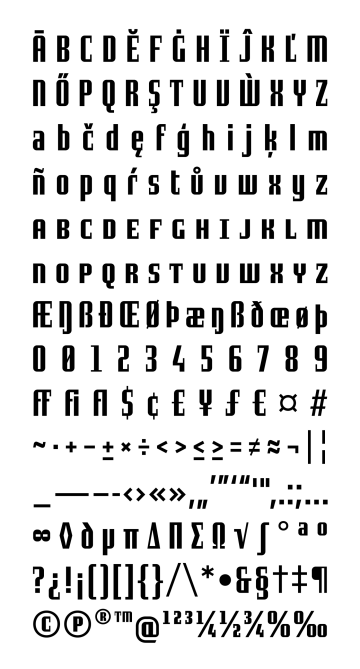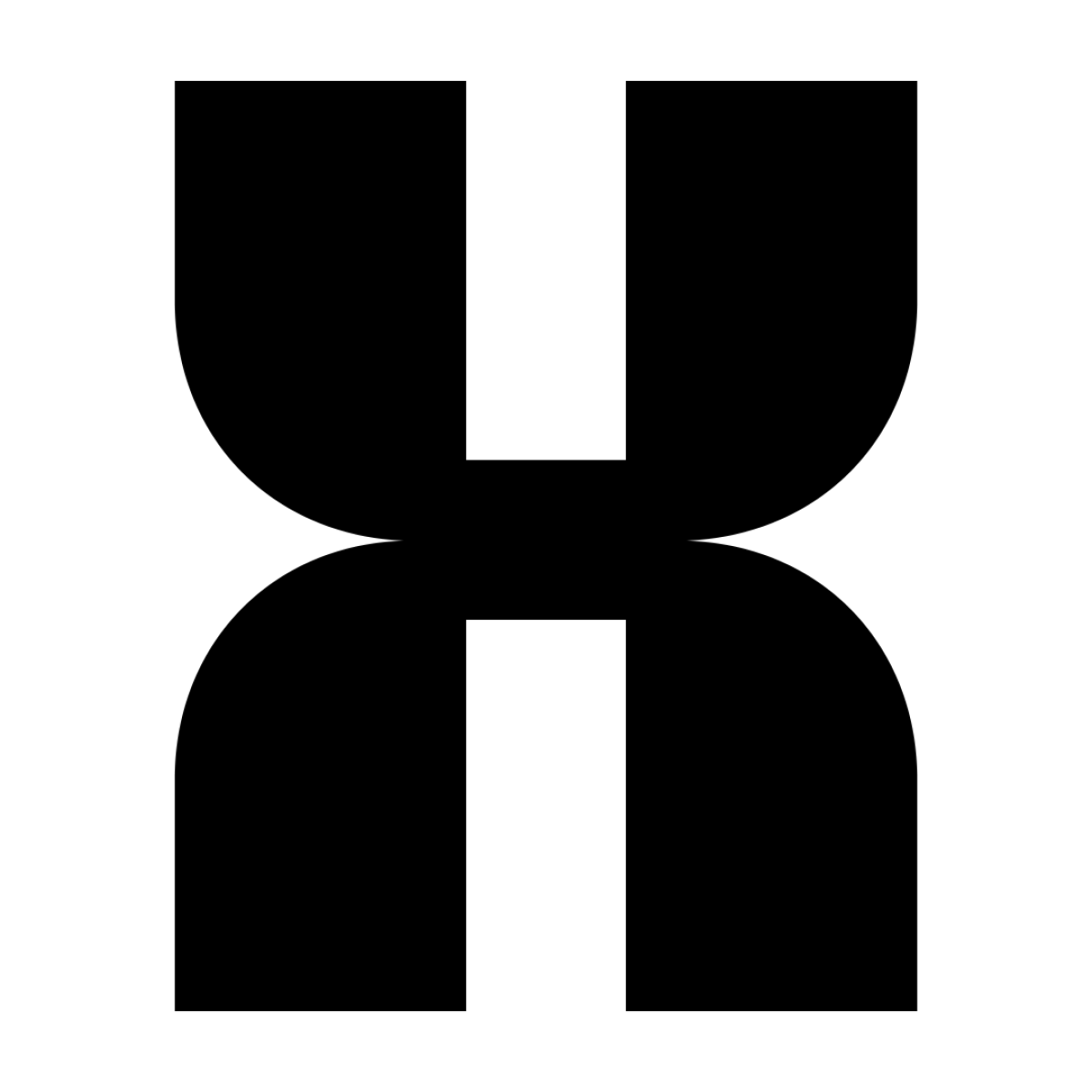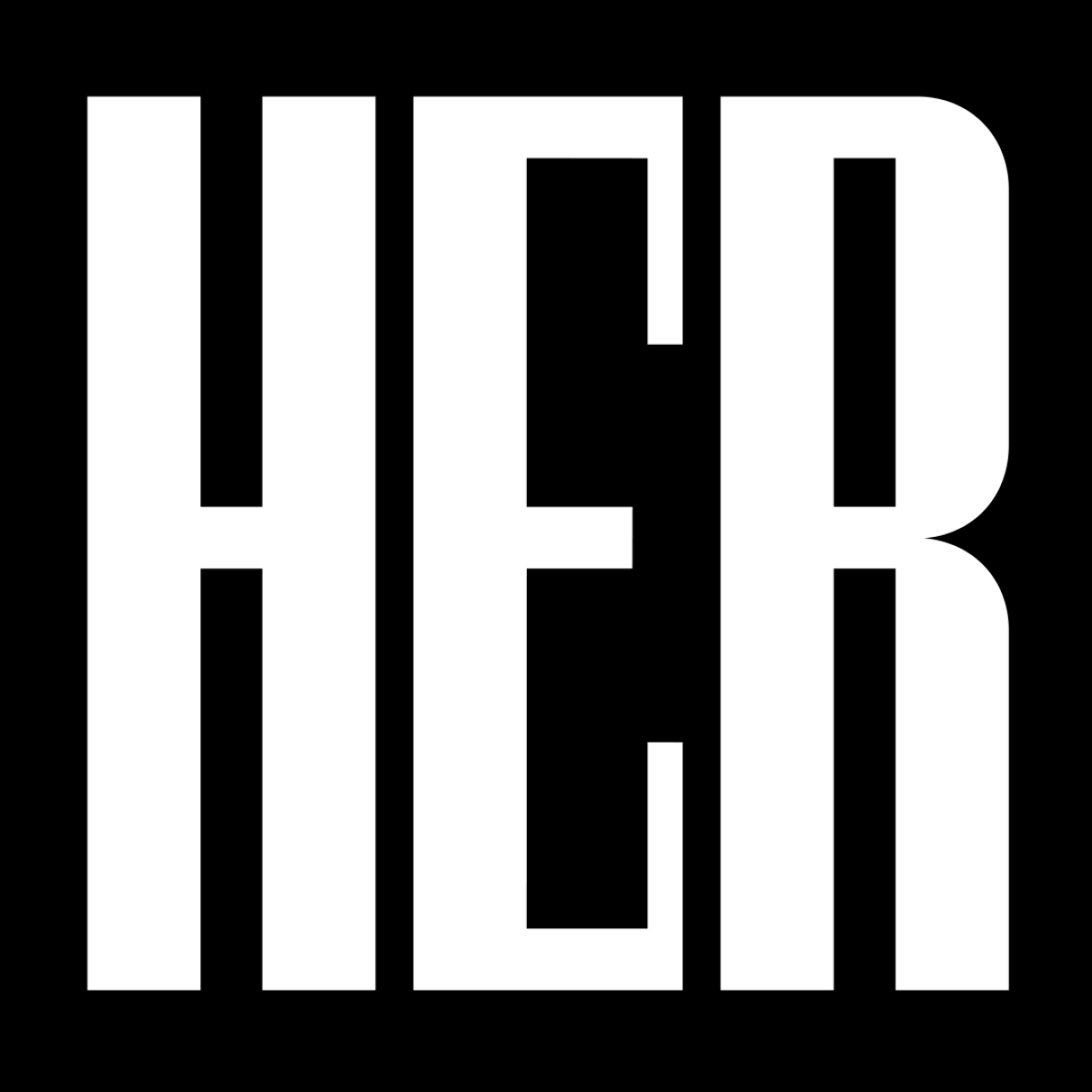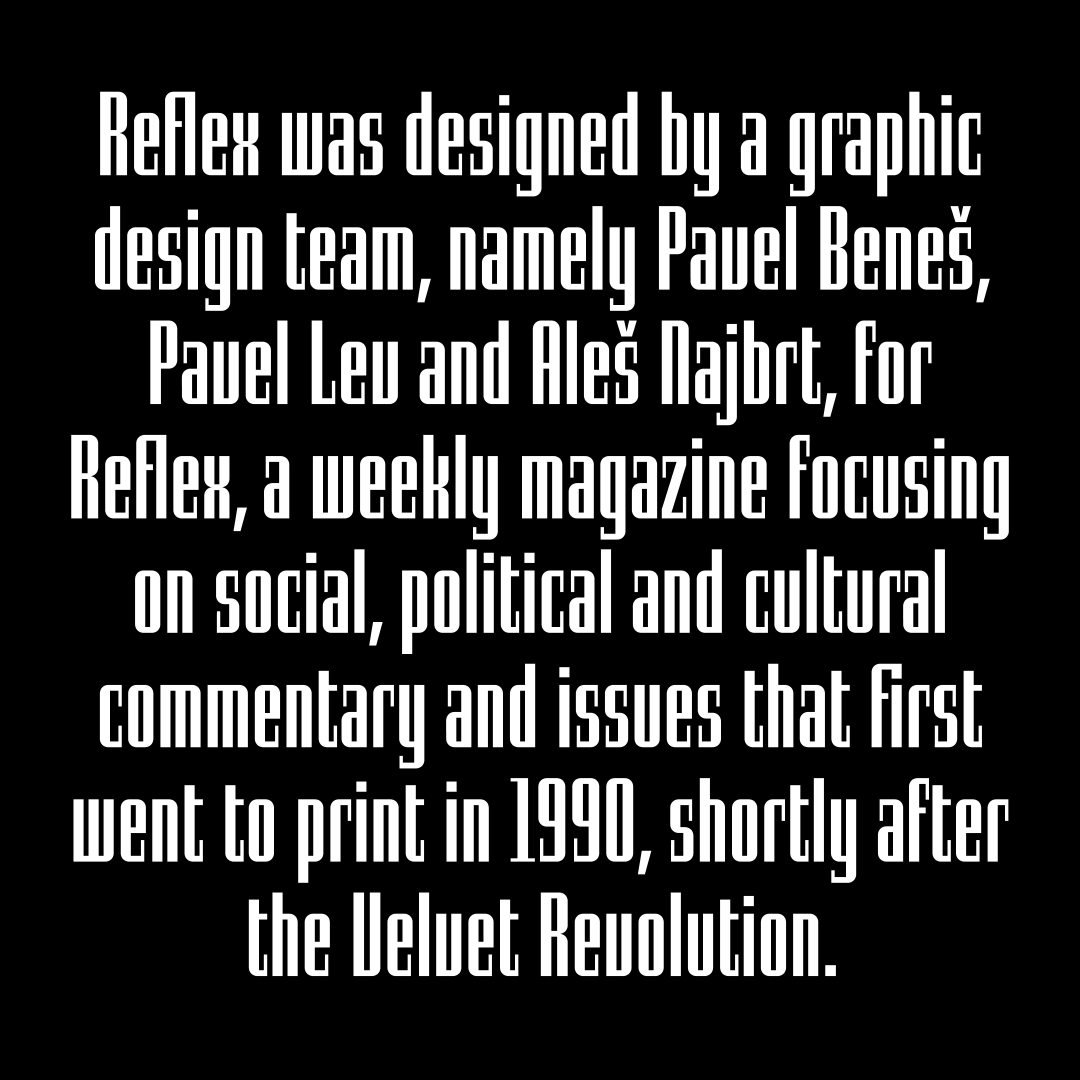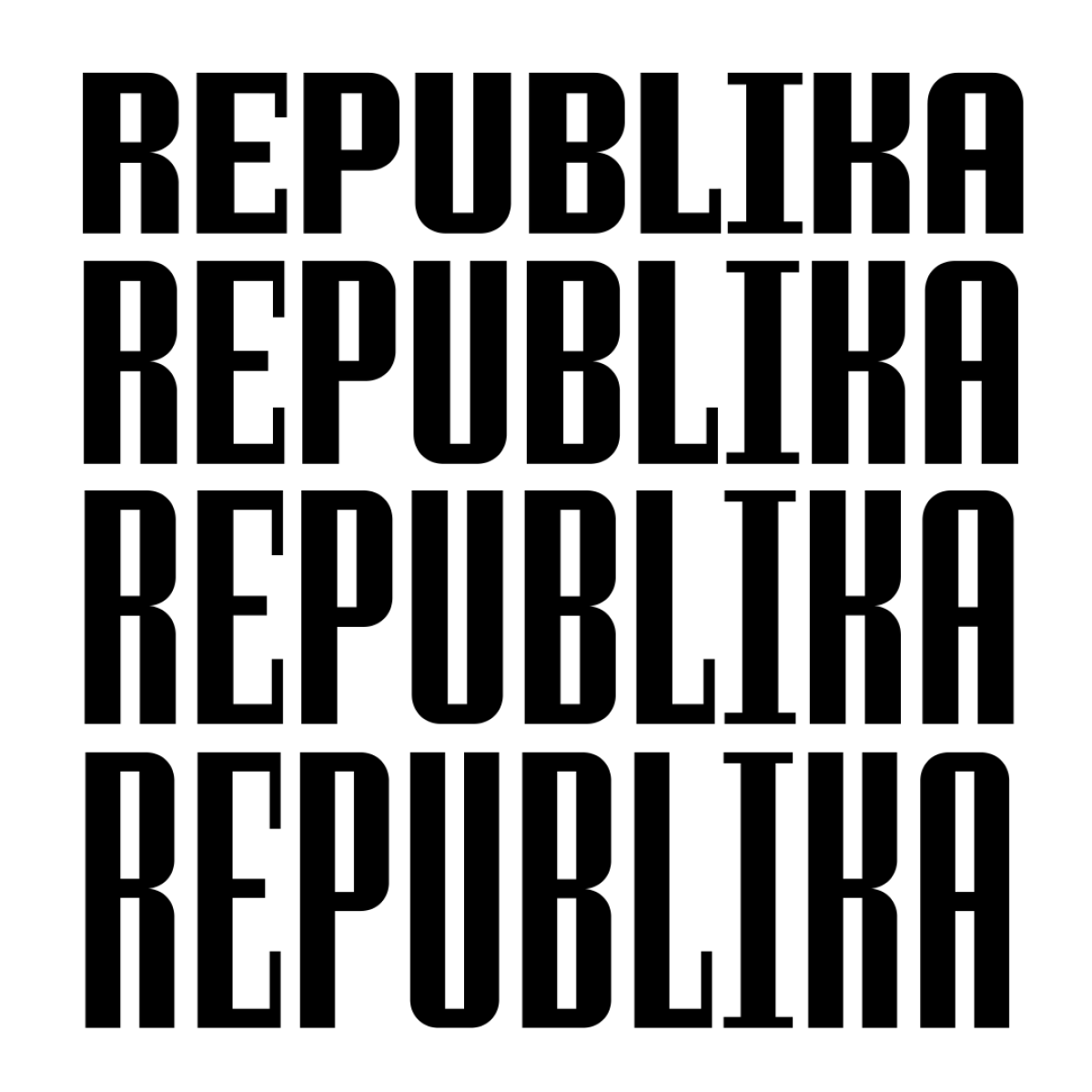
Reflex
Logo i způsob práce s obrazem, které Aleš Najbrt navrhnul pro první číslo společenského týdeníku Reflex z dubna 1990, se používá ve víceméně nezměněné podobě dodnes. Během tří let v pozici art direktora nakreslil desítky originálních titulků, ze kterých se někdy vyvinuly celé abecedy. Logo zůstalo zachováno, i když v roce 2001 časopis úspěšně redesignoval Marek Pistora a zahájil druhou slavnou éru magazínu. Potom, co se v roce 2011 Pistora připojil ke studiu, společně s Najbrtem písmo z loga dokončili, digitalizovali a používají dál. Reflex zastupuje kategorii geometricky konstruovaných písem, která se od podobně koncipovaných písem odlišuje především atypickými, tenkými svislými serify, neboli semi-serify. Vysoký kontrast a svislá stínová osa mu propůjčují neobvyklý charakter, který spolu se sníženými verzálkami a krátkými výběžky předurčuje Reflex pro účely titulkového písma. Ačkoli u takových písem není obvyklé, aby obsahovaly více jazykových sad a pokročilé funkce OpenType, Reflex je výjimkou. Disponuje nejen širokou škálou diakritiky, ligatur a zlomků, ale také řadou kapitálek s číslicemi, čímž de facto vytváří další šířkové proporce. Reflex nabízí pět řezů písma, od komprimovaného Extra Condensed po široký Extra Extended. Každá šířka je také doplněna kurzívní variantou, která kompenzuje absenci pravé kurzívy výrazným skloněním znaků, vycházejícího z úhlu naklonění písmene „L“ v logotypu.